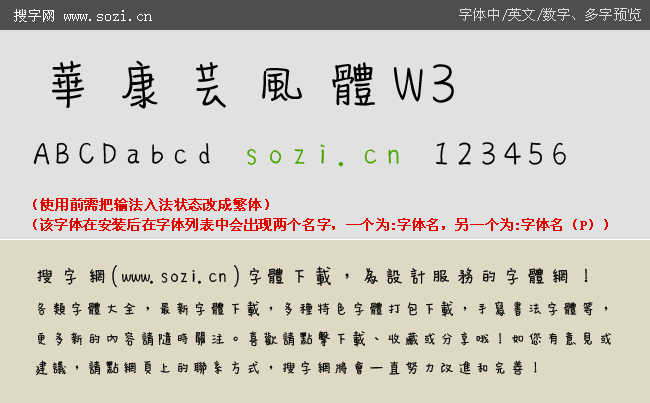
華康蕓風(fēng)體W3
搜字網(wǎng)提供一款手寫風(fēng)格的卡通字體下載,華康蕓風(fēng)體,這款字體是一款美術(shù)風(fēng)格的繁體字庫,摘自華康最新出品的《華康手書風(fēng)II-字得其樂》,字庫為大五碼(BIG5),臺港澳地區(qū)的繁體系統(tǒng)中使用,所以如果在簡體中文系統(tǒng)中使用時,必須直接輸入繁體字,才能正常顯示所有的文字,該字體模仿兒童的寫字風(fēng)格,童趣十足,適合兒童相冊、兒童畫冊、卡通畫冊等場合使用。